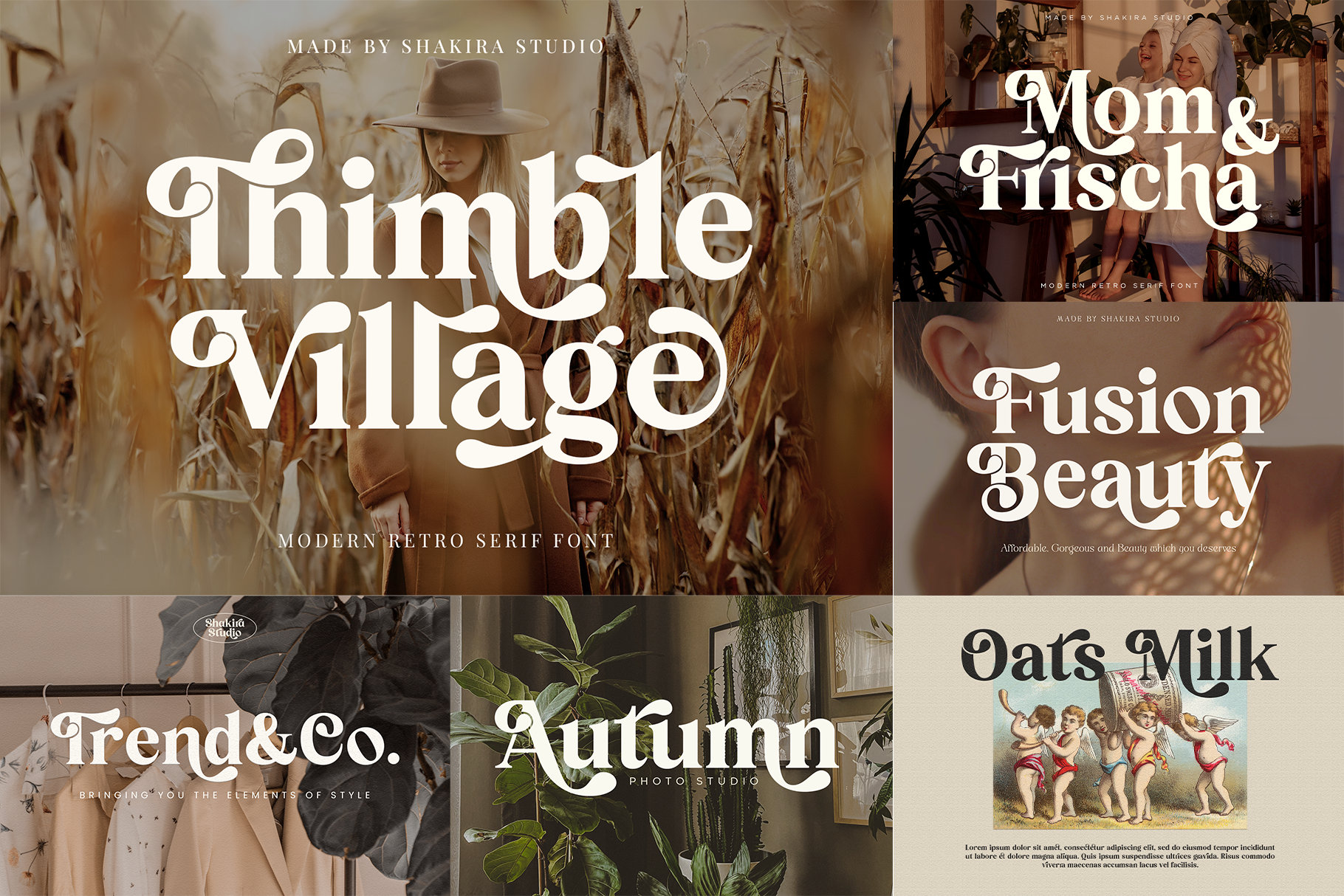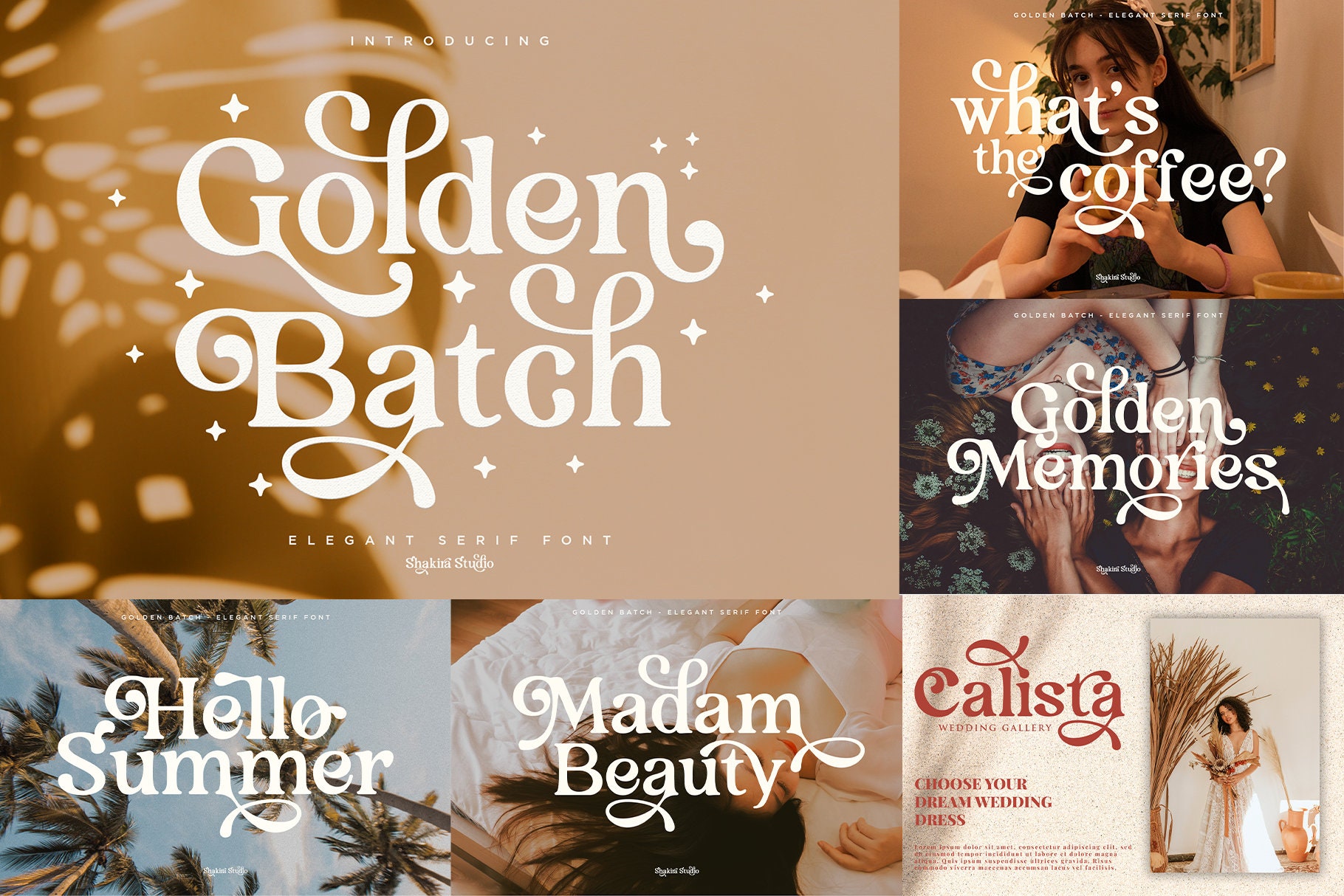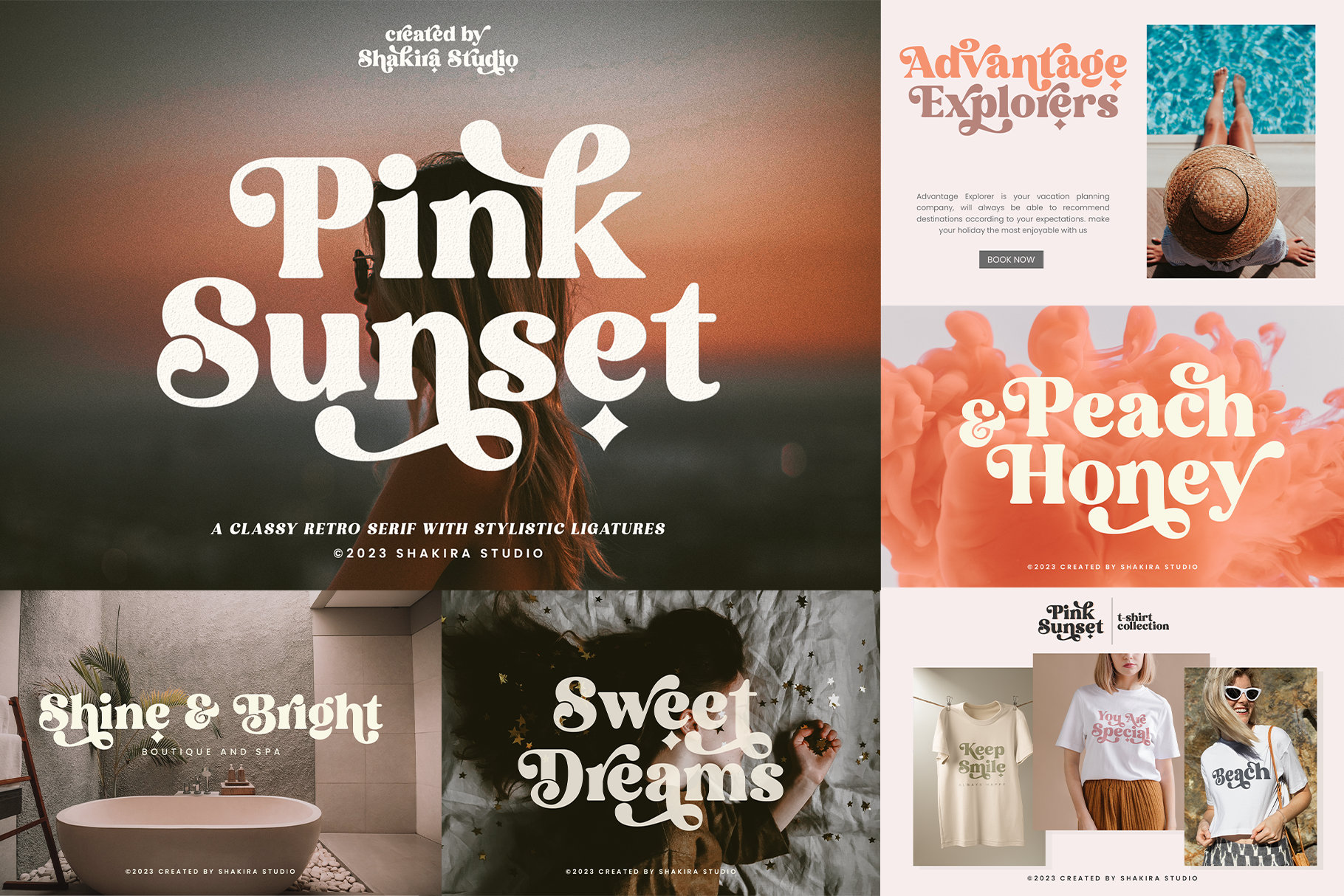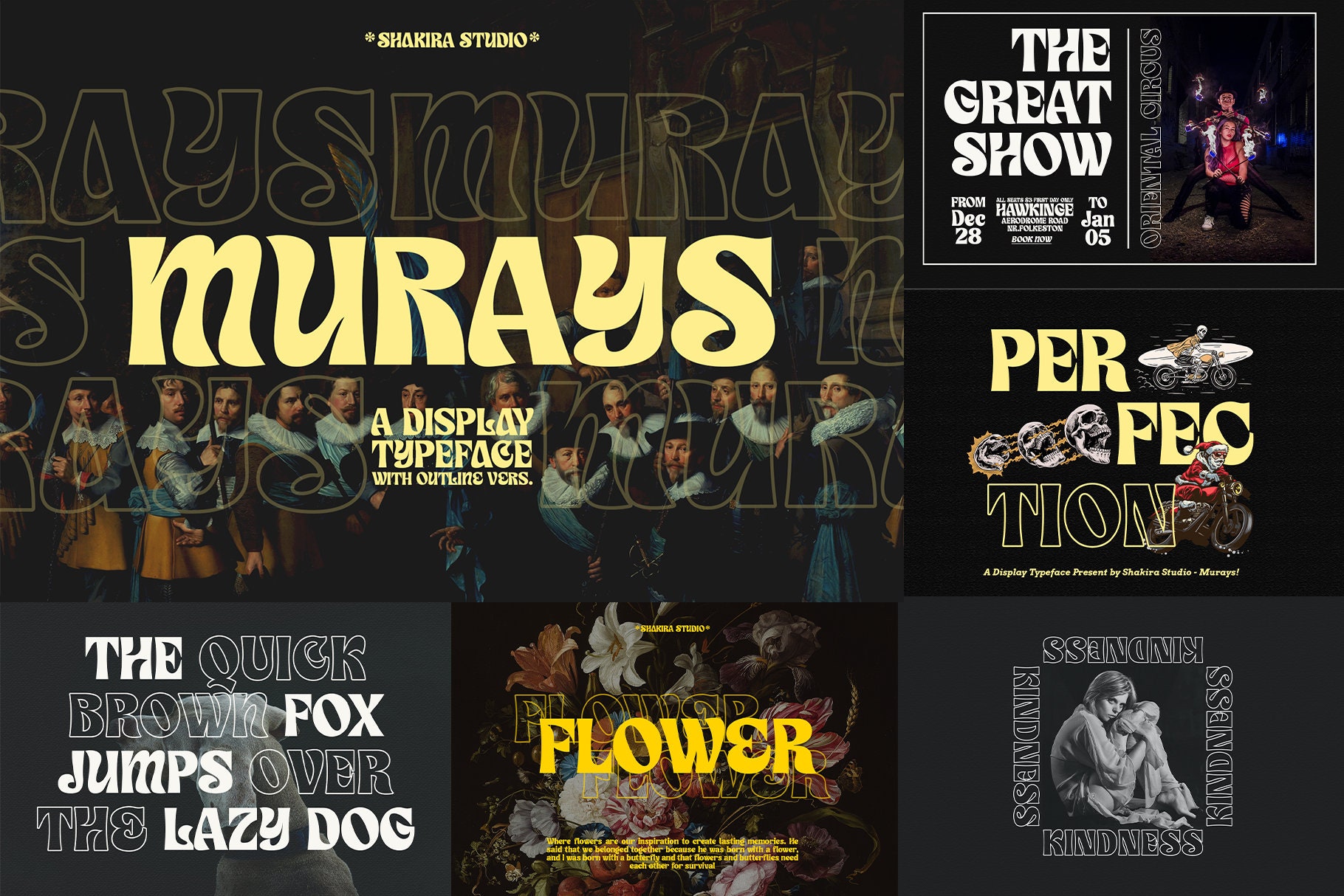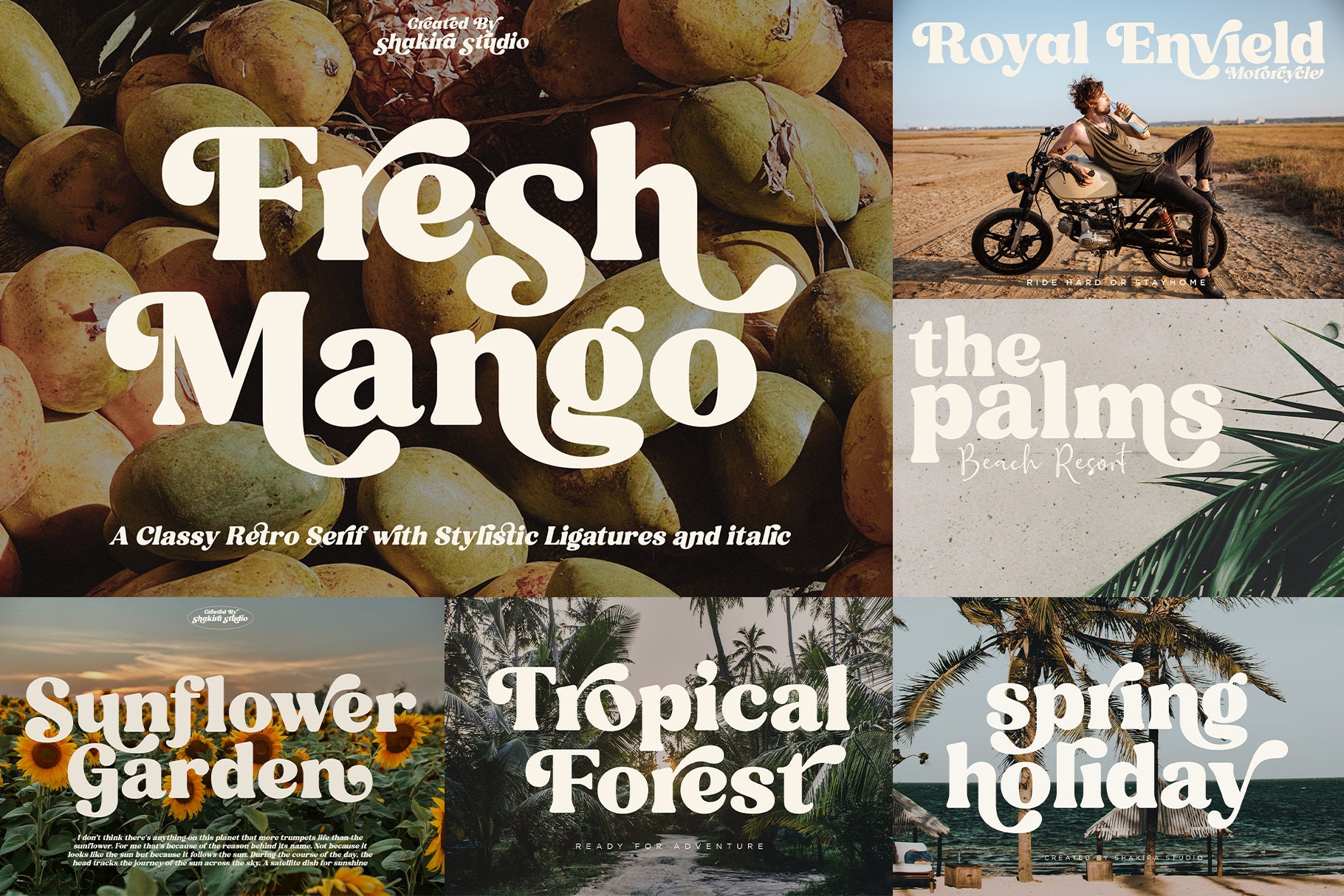
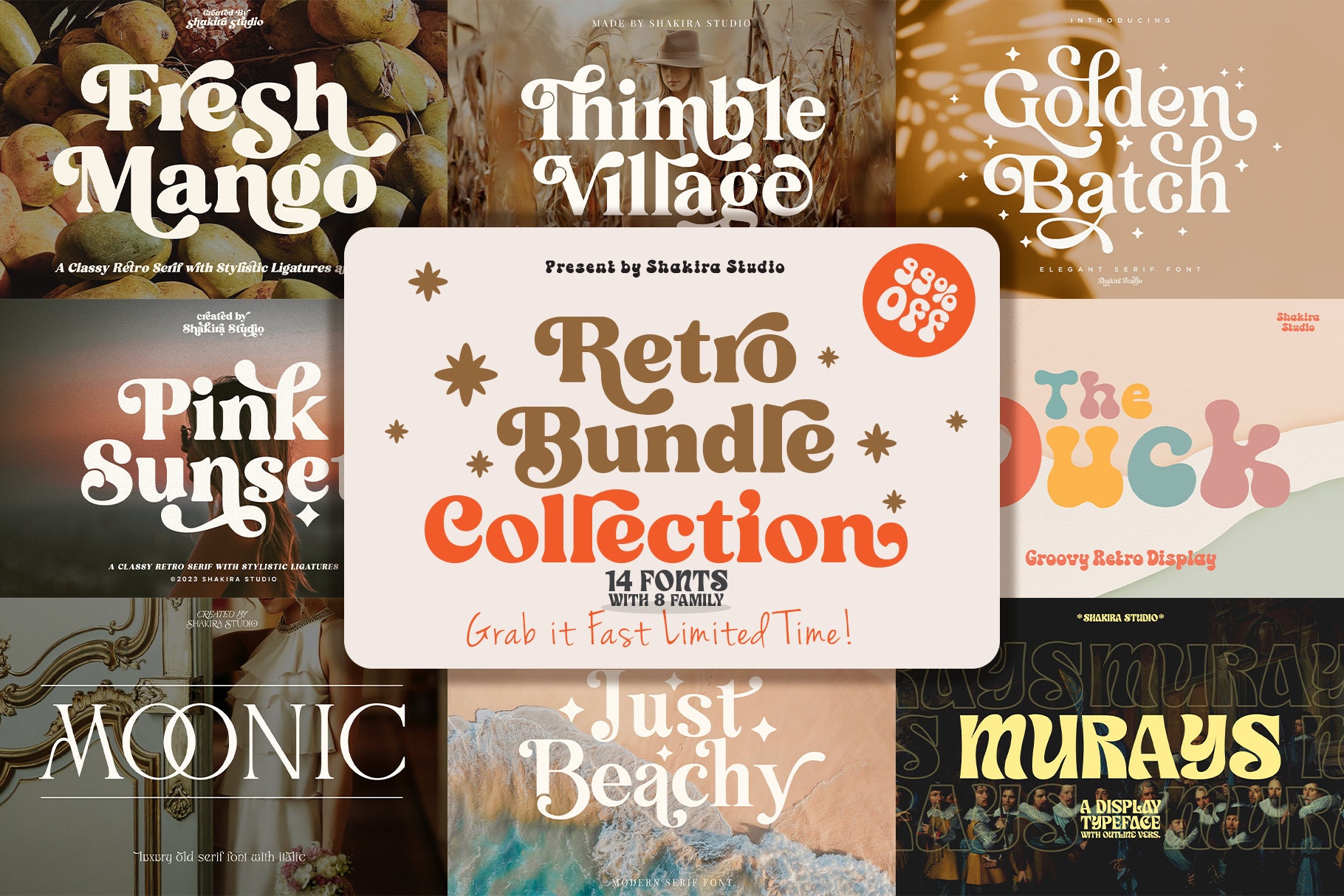
Modern Retro Font Bundle Collection – 14 fuentes para Cricut, Procreate, branding y diseño groovy
Descripción
Aporta un aire nostálgico a tus diseños con Modern Retro Font Bundle Collection: un kit tipográfico todo en uno para creadores que aman lo vintage con un toque moderno. Perfecto para usuarios de Cricut, artistas de Procreate, diseñadores de marca y makers DIY, este bundle reúne 14 fuentes dentro de 8 familias retro únicas, incluyendo serif, sans serif, display, script y estilos para titulares. Desde curvas setenteras groovy hasta encanto farmhouse y elegancia boho, tendrás todo para elevar logos, invitaciones, packaging, contenido social y más.
Por qué te encantará:
- Selección versátil: mezcla y combina serif, sans, display y script para construir sistemas tipográficos coherentes y con estilo.
- Pensado para proyectos reales: ideal para branding, logotipos, invitaciones de boda, carteles, revistas, gráficos de blog y plantillas para redes sociales.
- Amigable con Cricut y Procreate: crea archivos de corte, calcomanías y letras con apariencia manuscrita gracias a curvas suaves y contornos limpios.
- Retro en clave moderna: estéticas groovy, boho y farmhouse adaptadas a las tendencias actuales.
- 14 fuentes premium agrupadas en 8 familias retro distintas
- Alternativas, swashes y caracteres estilísticos en fuentes seleccionadas para un lettering expresivo
Crea tipografías atemporales y llamativas en minutos: ya sea un logo retro, un titular estilizado o un letrero farmhouse con encanto. Modern Retro Font Bundle Collection te da la libertad de explorar, experimentar y diseñar con confianza.